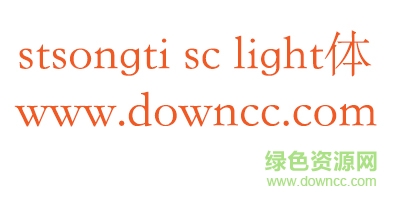
stsongtisclight字體也就是華文宋體細(xì)體。華文字體在字體庫中一直都很受歡迎!這款stsongtisclight字體生動靈秀,適用范圍廣泛。需要的朋友歡迎在綠色資源網(wǎng)下載!
stsongtiscligh字形清秀,筆畫纖細(xì),字型優(yōu)美生動,該字體常常用于蘋果操作系統(tǒng)!